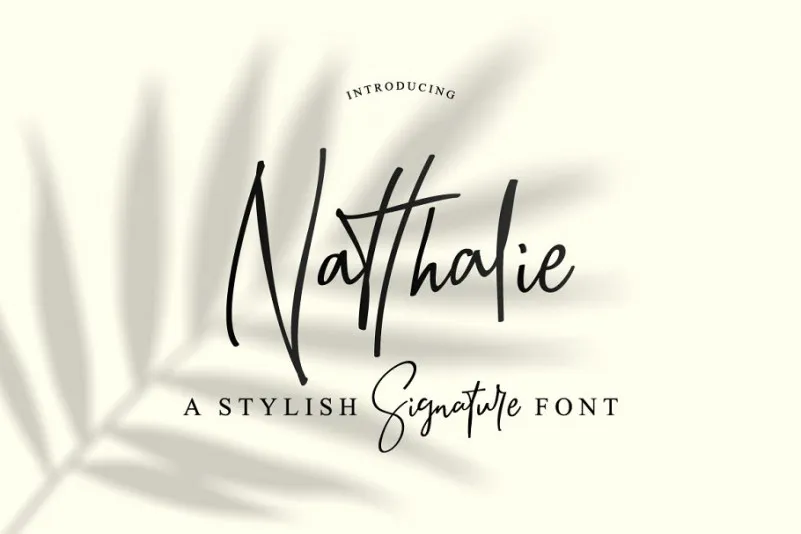
Natthalie Signature Font – Fonte Grátis
Natthalie Signature Font
A Natthalie Signature é uma nova opção no mercado de fuentes script, ideal para designers que buscam expressar elegância e modernidade em seus projetos. Esta fonte foi criada por pointlab e se destaca pela sua combinação perfeita entre a grafia cuidadosamente elaborada e o estilo contemporâneo da escrita manuscrita. Natthalie Signature é mais do que apenas uma opção de design para criar texturas sofisticadas; ela oferece um formato vibrante e moderno, com características únicas como caracteres decorativos e uma linha de base que flutua elegantemente, criando assim um visual único. Ideal para aplicações de eventos sociais, logotipos, cartões de visita, cartazes e até mesmo mensagens quotidianas, a Natthalie Signature se destaca por sua versatilidade e facilidade de uso, tornando-a uma escolha inteligente para designers que desejam incorporar um toque especial em seus projetos.